今回は「待」の書き方を解説します。
「待」の見本
「待」の書き順
9画です。
「待」の構成
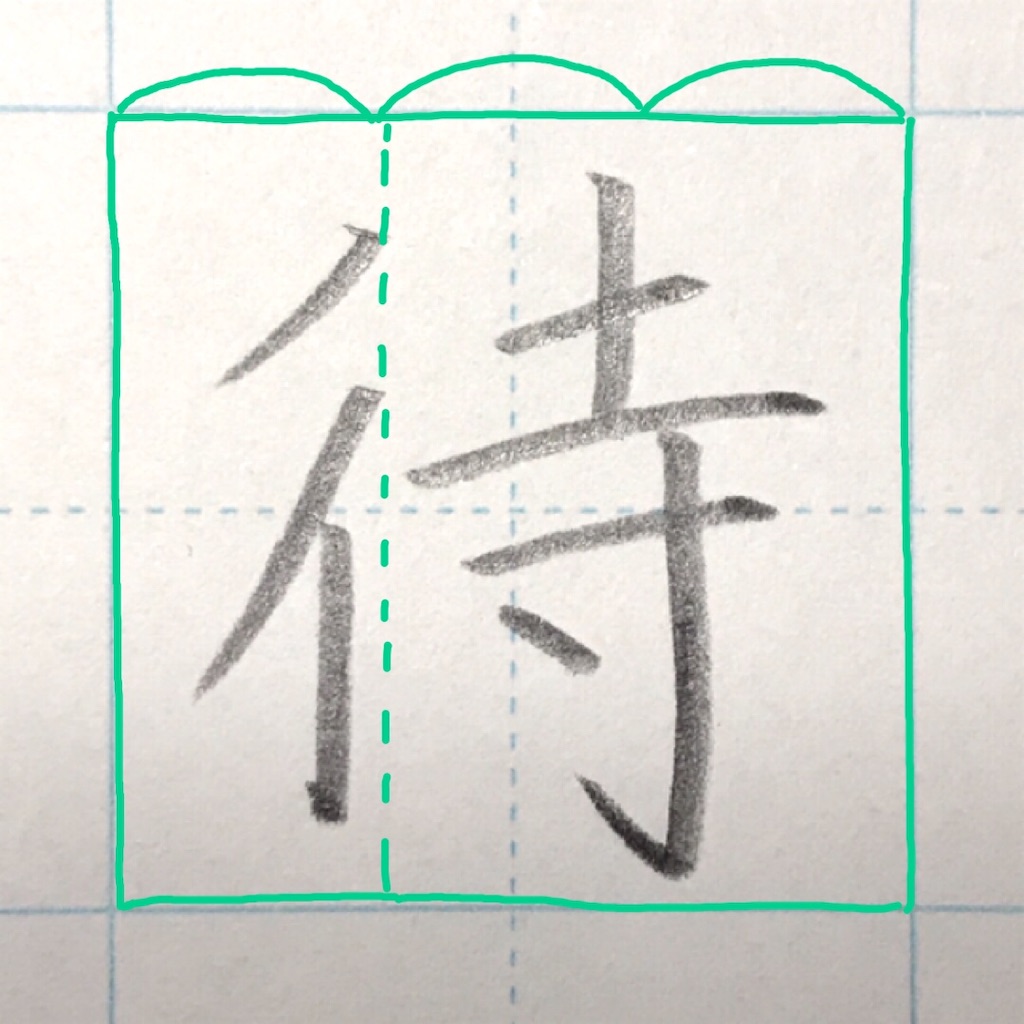
「へん」と「つくり」の大きさを1対2の割合にしましょう。
「待」のポイント
【重要】
「ぎょうにんべん」の書き方、ぜひいろんな字に応用してください(o^^o)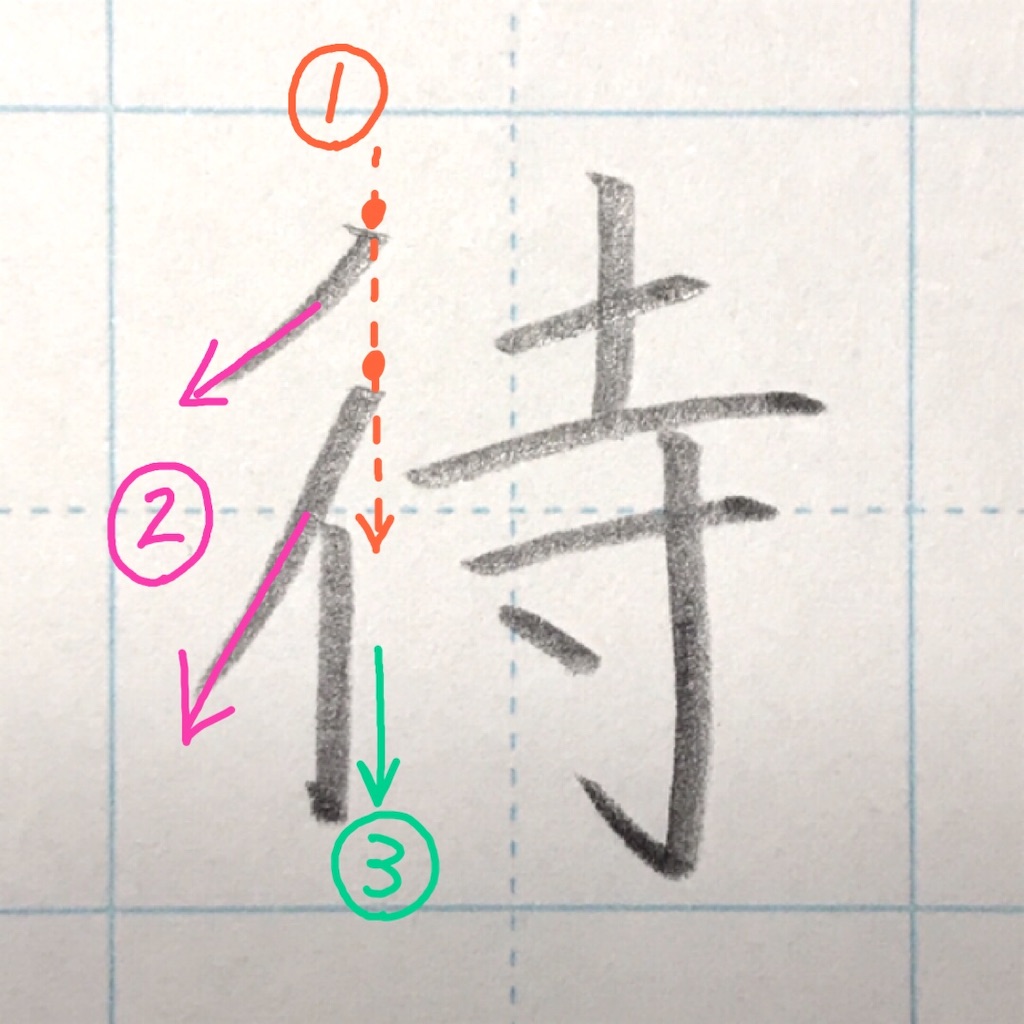
①1画目と2画目のスタートは、縦にまっすぐ揃える。
②1画目と2画目の払いは、それぞれ角度を変える。
→1画目は45度くらい、2画目は少し広がるように。
③2画目の上の方から、まっすぐ。
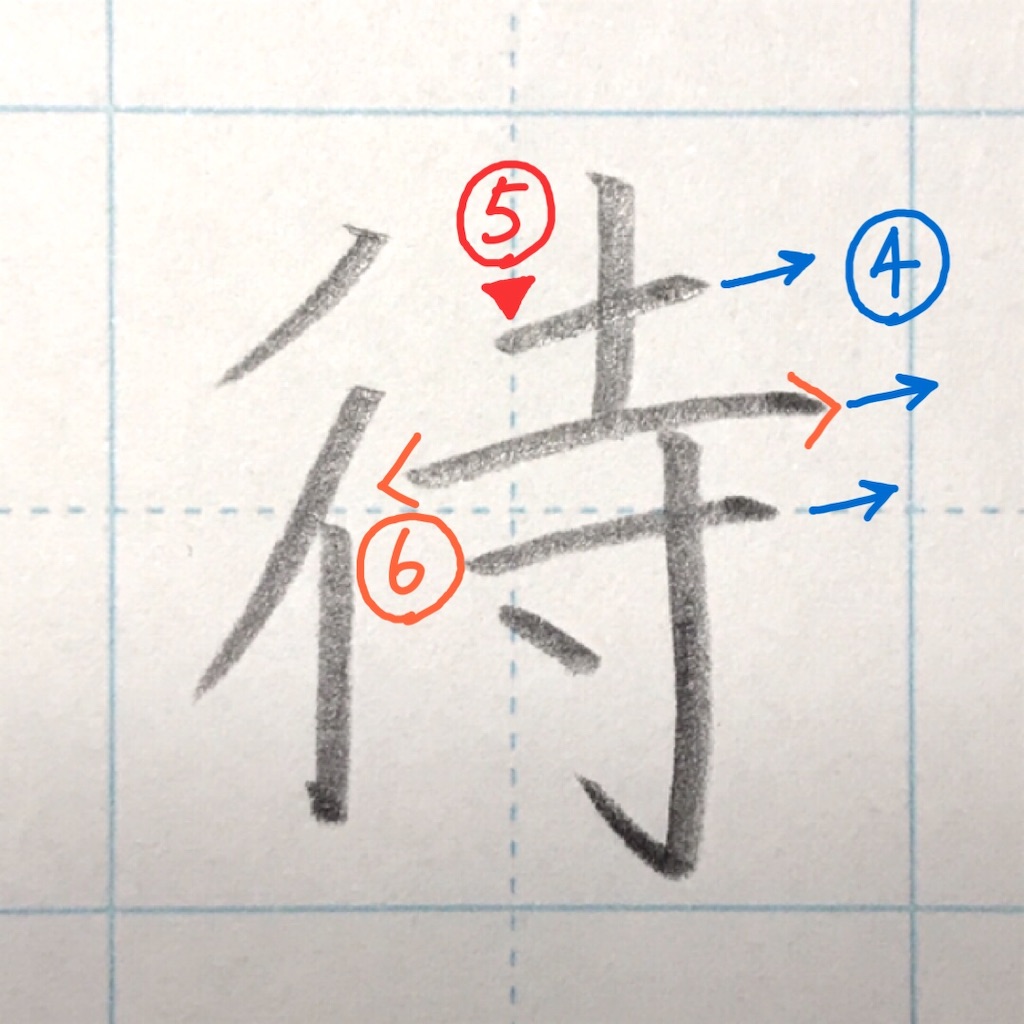
④横画は右上がりに揃えるときれいです。
⑤4画目は中心線からスタート。
(白紙に書く場合も位置を確認して、ここが中心にくるように。)
⑥6画目、長く強調。
⑦ぎょうにんべんより少し高く。
⑧間隔を等しく。
⑨8画目は、7画目の2対1のポイントを通る。
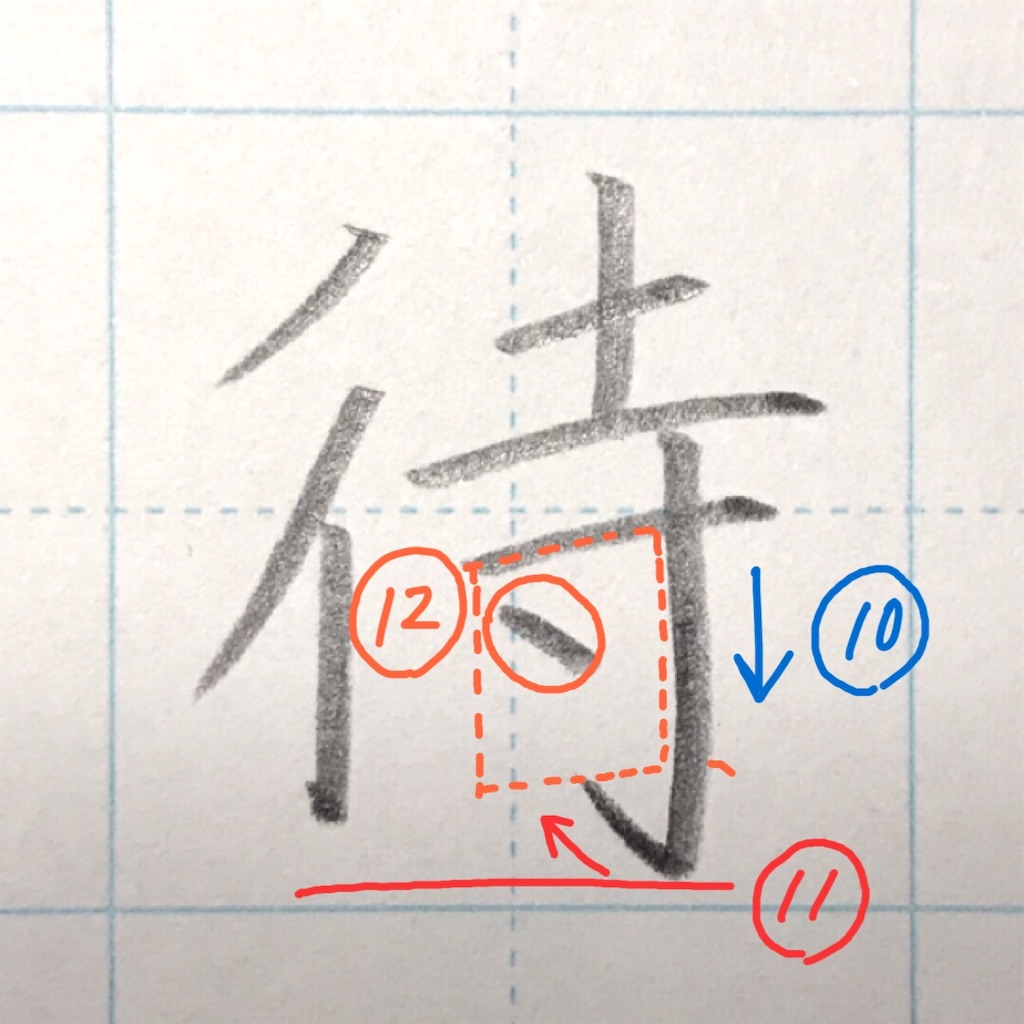
⑩まっすぐ、曲がらない。
⑪ぎょうにんべんより少し低く。
次の画に向かって、しっかりとハネる。
(45度くらいが◎)
⑫点は、点線の空間の左上に打つ。
(45度くらいが◎)
完成!